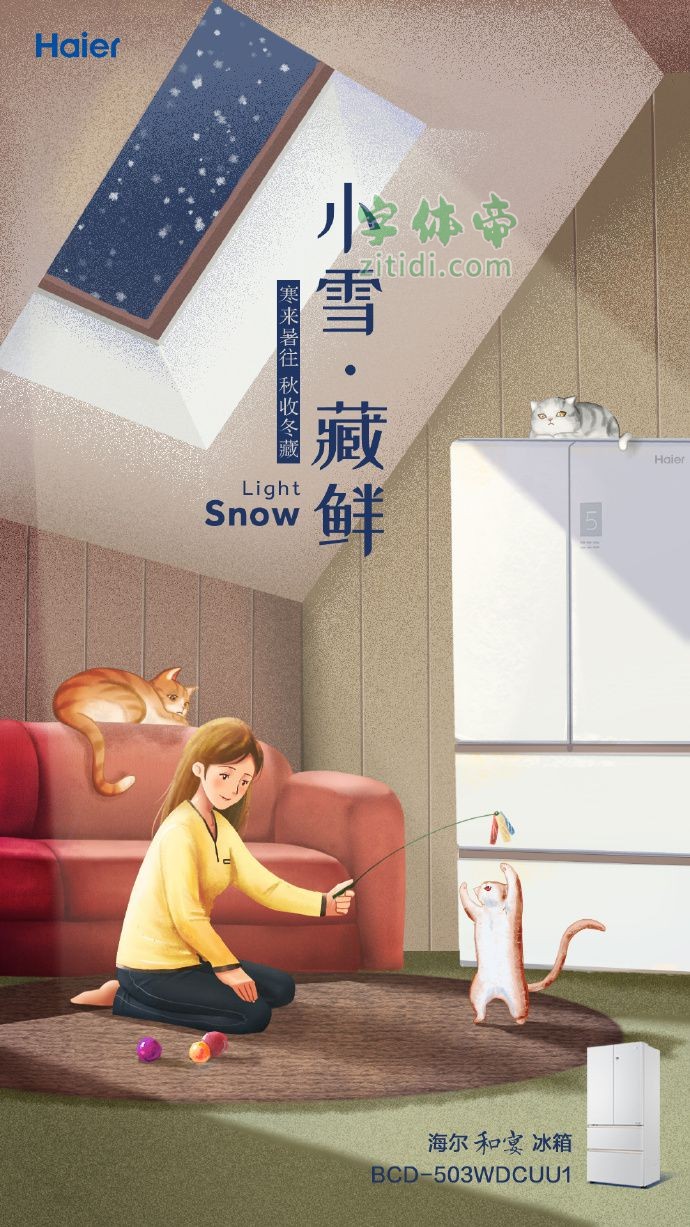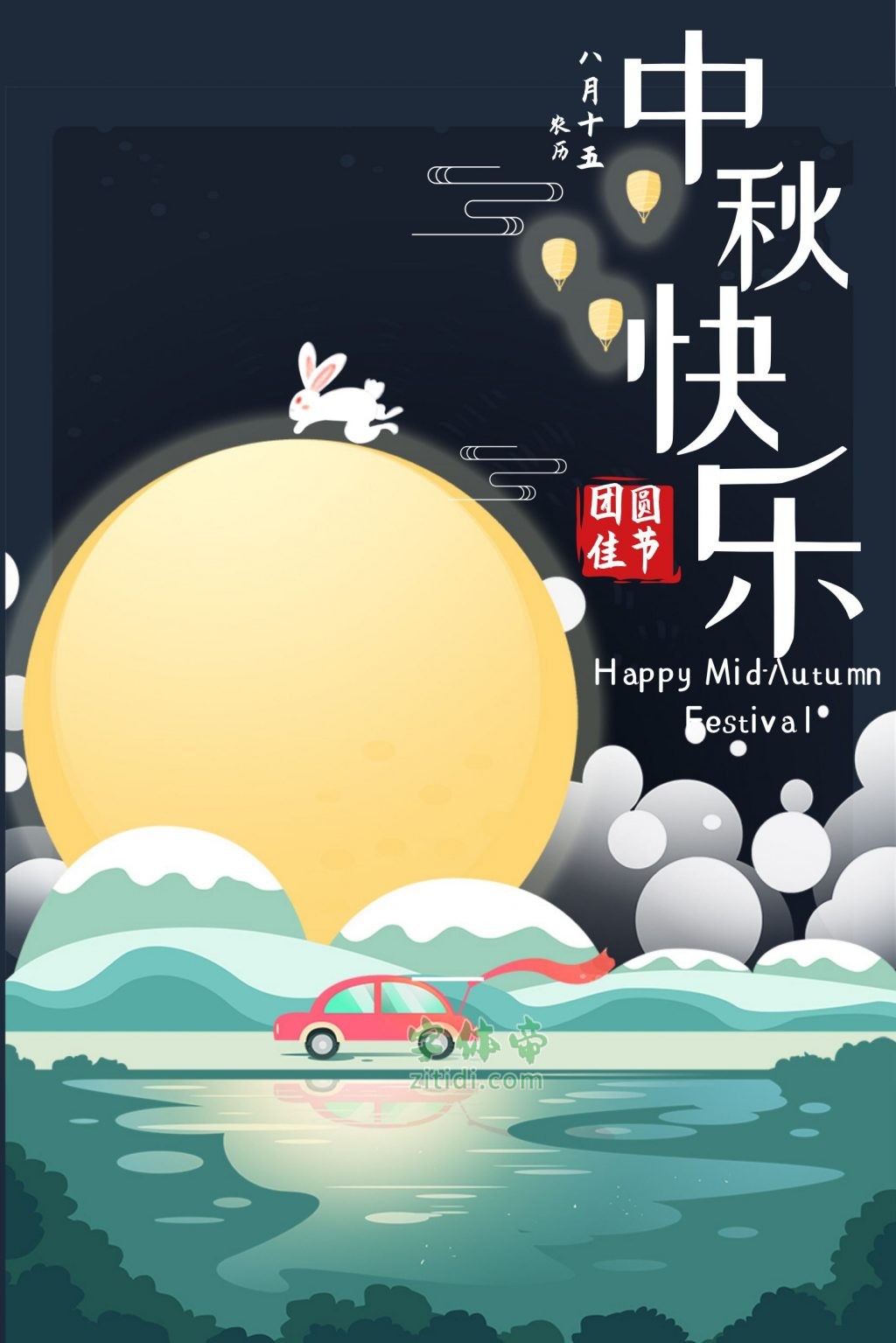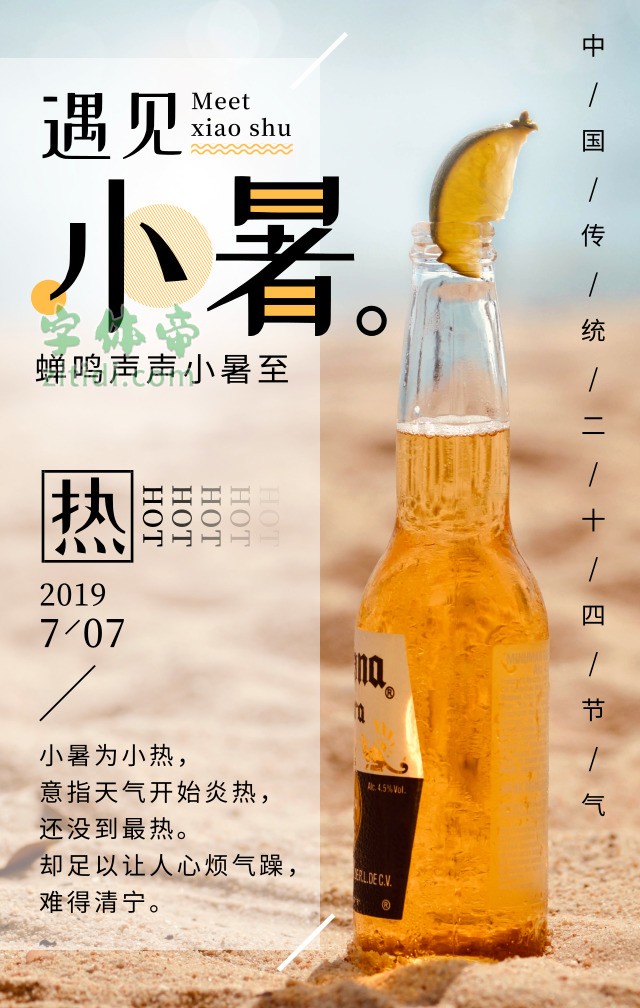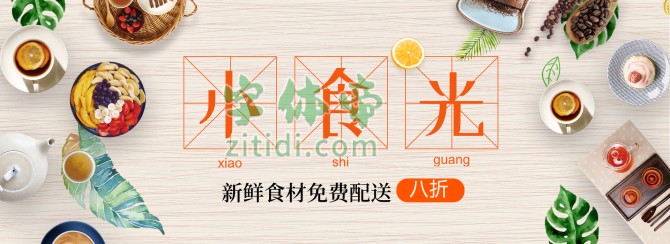
「 站酷小薇LOGO体 」是李大卫送给自己女儿出生三周年的一个礼物。 由上海佐兹品牌设计工作室设计总监李大卫 (David 小马哥)带领其工作室团队共成完成。 其目的是为了填补免费字体中的LOGO体空缺。字体笔画浑厚,识别性高,放大放小空间间隙都能如意灵通。2018年1月最新修订版。
字体特色
「 站酷小薇LOGO体 」 设计大胆创新,笔画与剑身相似,修长、谦和、灵秀,在简略了一些原字笔画的同时依然保持了很高的识别性,是标志,标题的神器。采用GB2312汉字编码,共收录6763个汉字。免费授权全社会使用(包括商用)。
“站酷小薇LOGO体”是一款书写很新颖的字体,字体大方,适合各种设计作品使用!欢迎下载!